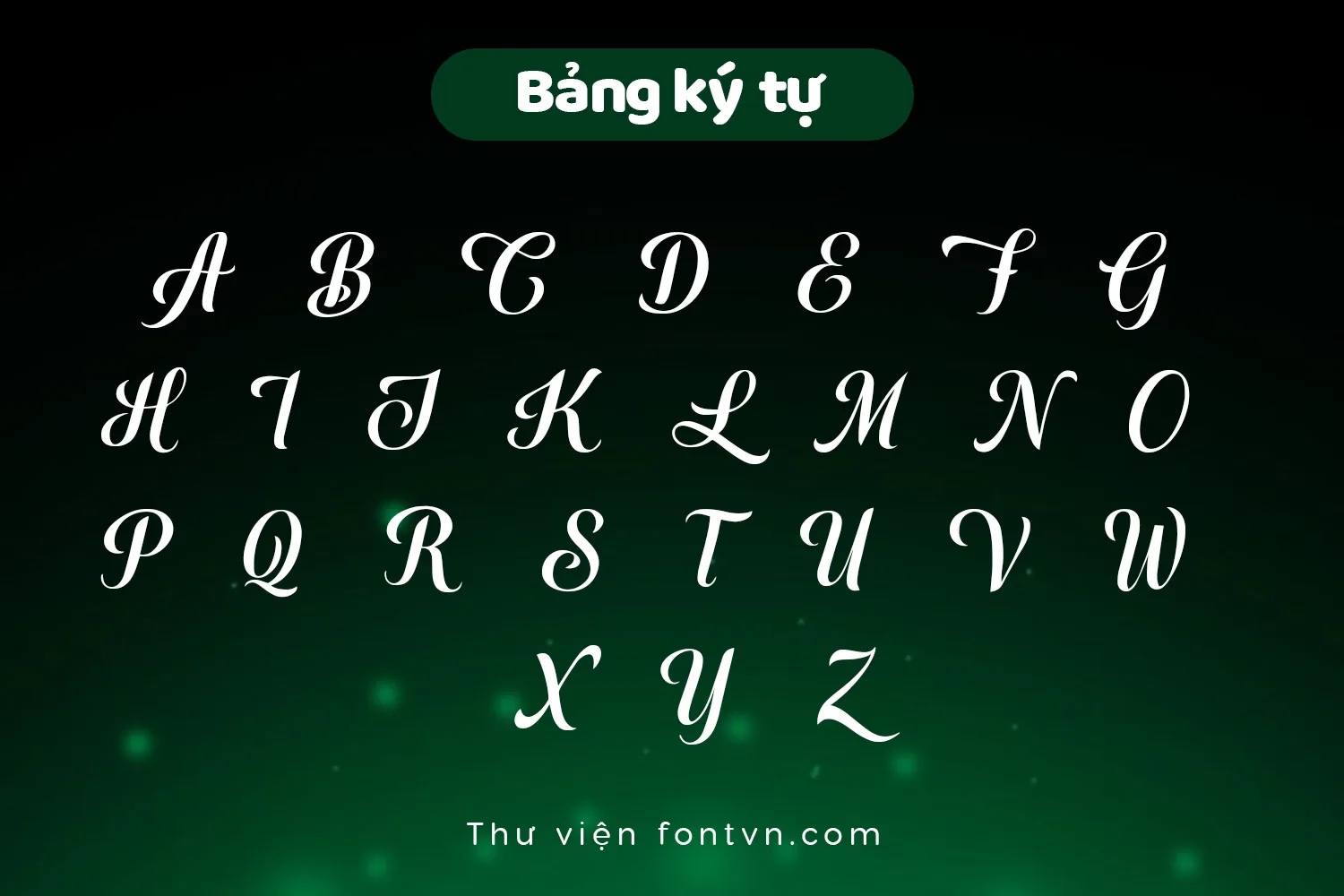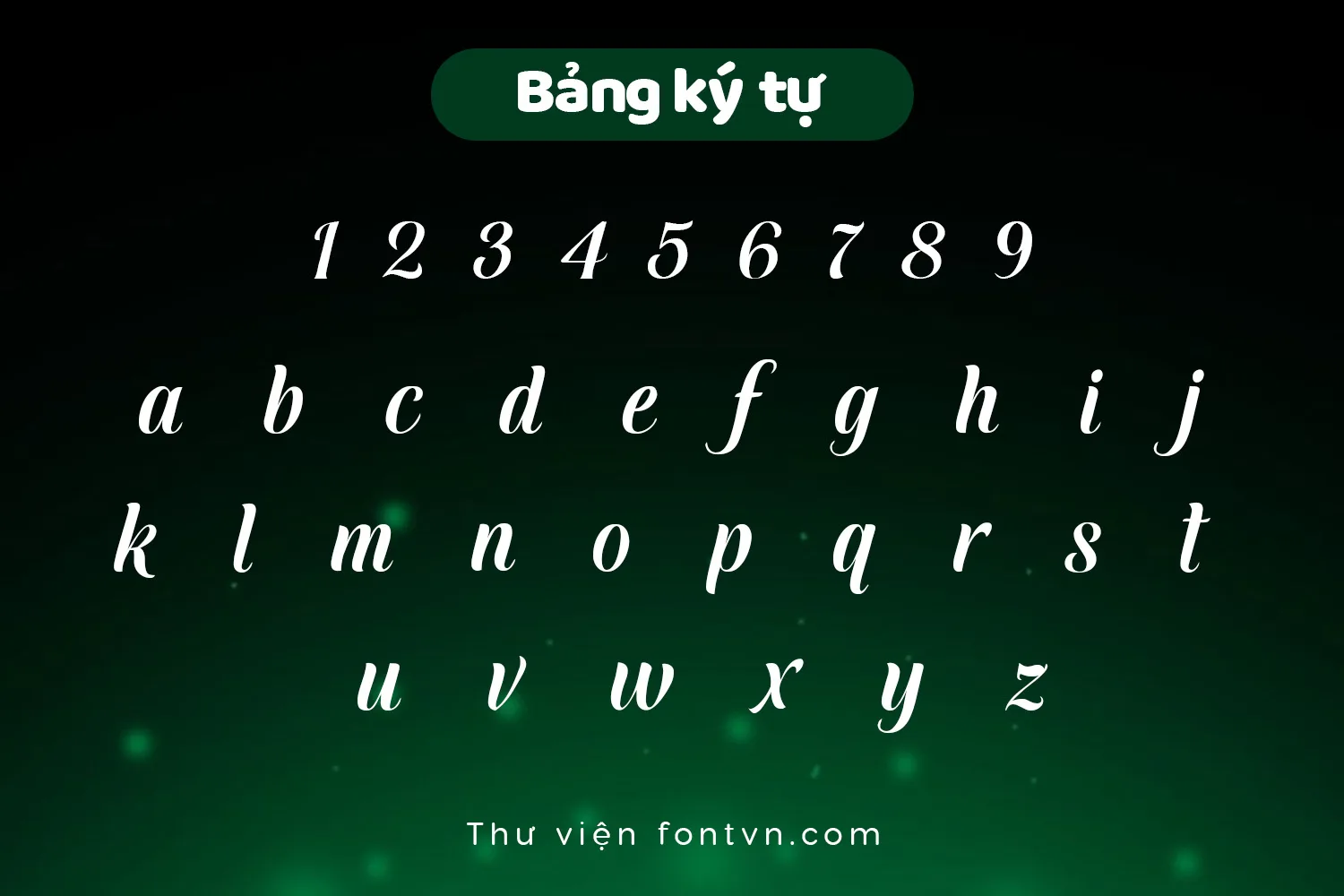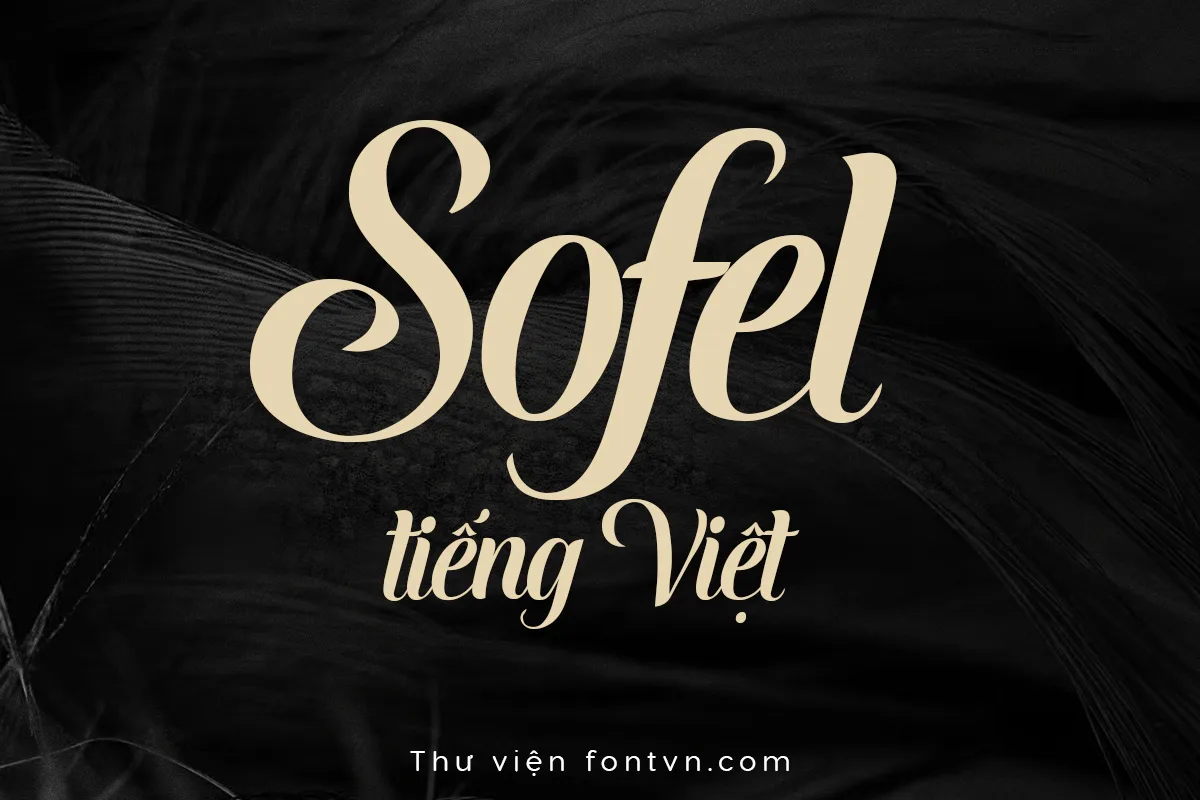
DVN – Sofel tiếng Việt – Calligraphy Cổ Điển & Sang Trọng
DVN – Sofel là một font chữ mang đậm phong cách Calligraphy truyền thống, nổi bật với sự tương phản rõ rệt giữa những nét thanh mỏng manh và nét đậm dứt khoát, mô phỏng hoàn hảo kỹ thuật viết bút máy ngòi lá tre. Trong khi các chữ cái in hoa được thiết kế cầu kỳ với những đường cong uốn lượn đầy tính nghệ thuật, thì các ký tự in thường và bộ số lại duy trì độ nghiêng mềm mại đồng nhất, tạo nên một tổng thể vô cùng uyển chuyển, thanh lịch và lãng mạn.
Nhờ vẻ đẹp sang trọng và tinh tế, font chữ này là sự lựa chọn lý tưởng cho các ấn phẩm đòi hỏi tính thẩm mỹ cao và sự trang trọng. Nó đặc biệt phù hợp để thiết kế thiệp cưới, logo cho các thương hiệu cao cấp như thời trang hay mỹ phẩm, thiết kế bao bì sản phẩm mang hơi hướng cổ điển, hoặc làm điểm nhấn nghệ thuật trên các ấn phẩm mang phong cách vintage.